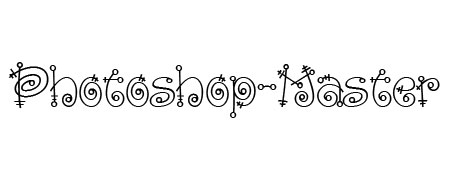
Дополнения Шрифты Татьяна Гапонова 7 августа 2009 Шрифт - Fairytale Интересный шрифт без поддержки русского языка. Скачать Шрифт - Fairytale
прикольно)
красивый шрифт
Прикольный! спасибо)
вообще классный шрифт!
Хороший шрифт.
ух ты такой красивый))спасибо большое!
Милая фигнюшка. Очаровательно)
Жаль только на инглише...
Замечательная фигня, аригато!)))
на антенны похож)
Вау...прям как в городе роботов...классная хрень,спасибо)))